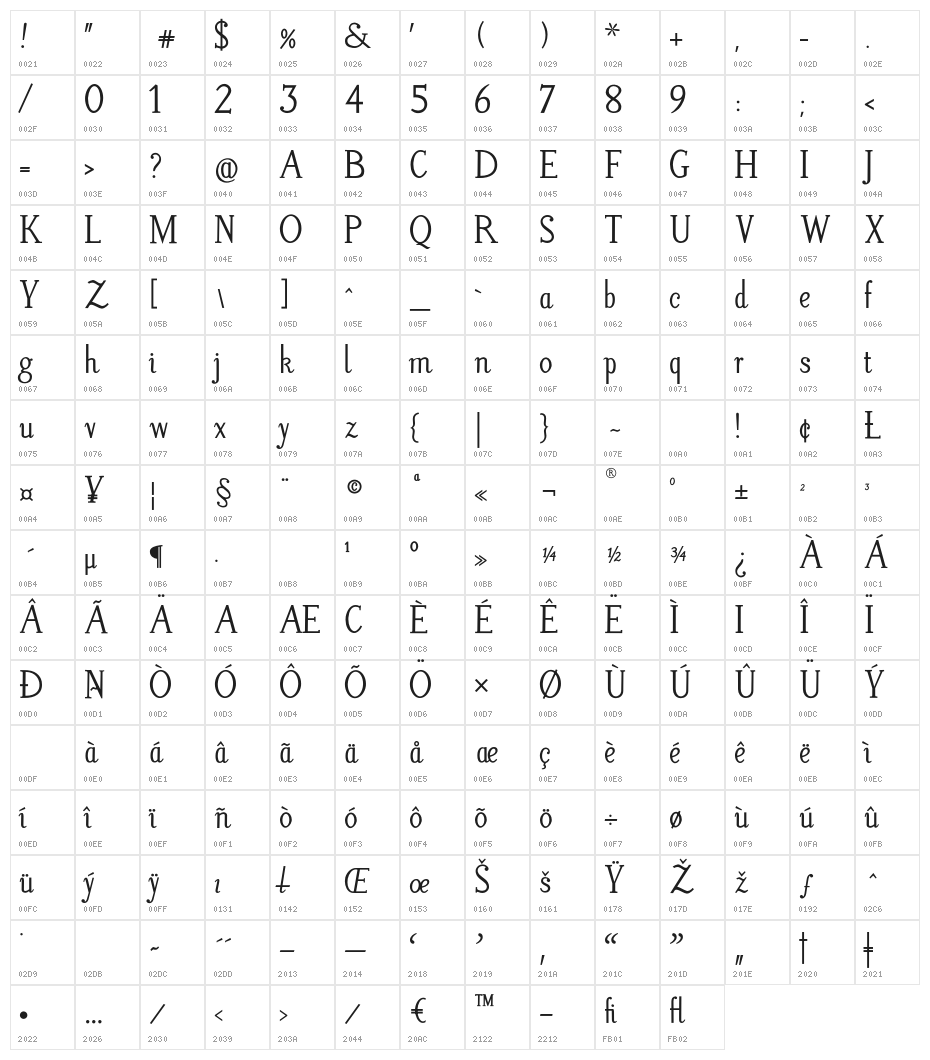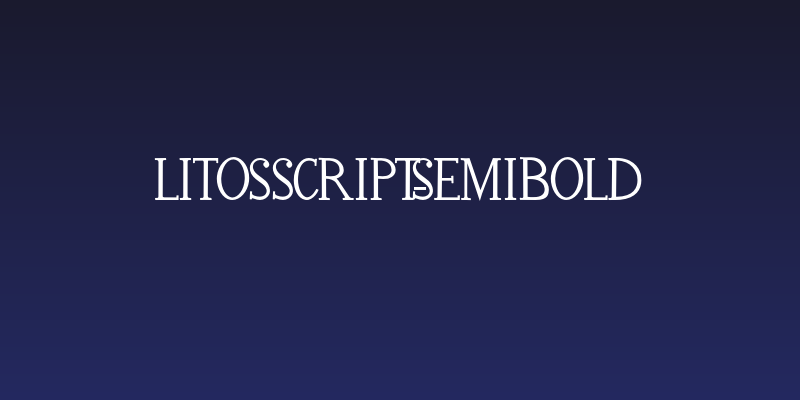
LitosScript-SemiBold Font
| Nom | LitosScript-SemiBold |
| Poids | SemiBold |
| Catégories | Script |
| Style général | Elegant |
| Cas d'utilisation | Headlines, Invitations, Branding |
| Projets proposés | Ideal for wedding invitations, elegant branding, and sophisticated editorial design. |